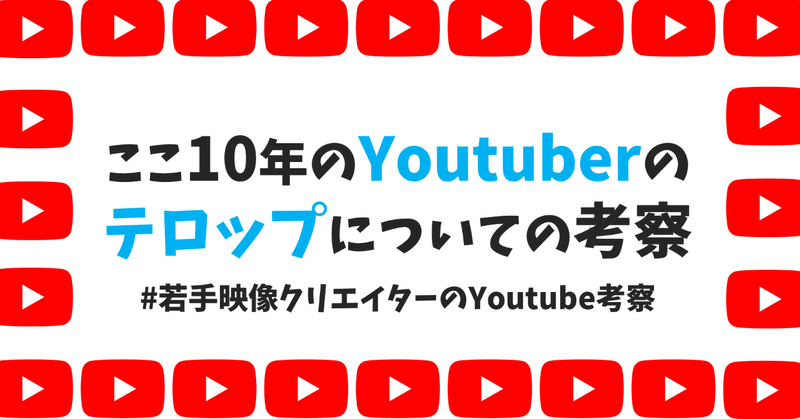
テロップ フォント
テロップを入れた時に、四角く文字化けしてしまう時は フォントを日本語に変える と入力できます。 テロップのフォントは、ソースパネル内のエフェクトコントロール→テキスト→ソーステキストで変更可能です。 テロップに色をつける.
テロップ フォント. YouTuberにもオススメ!映像・動画、テロップにオススメのフォント・書体を紹介 書体をテロップで見かける縁取りにしてみた「明朝体」編 書体をテロップで見かける縁取りにしてみた「ゴシック体」編 明朝体7ウェイトがフリー(無料)で使えるオープンソースフリーフォント「源ノ明朝. テロップを少し意識して見やすくするだけでも 動画のクオリティは一気に高まります! 今回は動画制作者向けに 読みやすいテロップの作り方の例を紹介したいと思います。 フォント サイズ 太さ 色 背景 装飾 レイアウト 行間 カーニング 改行 表示時間. 使用フォント:游ゴシック体 Bold ↓アピアランス設定↓ 左下の「新規線を追加」「新規塗りを追加」「新規効果を追加」ボタンからすべて作成していきます。 テロップ例その2:ハッキリしていて読みやすいデザイン 2つ目は、縁や影が強い固めのデザイン.
さっそく日本語のフリーフォントで商用利用可能なものを教えてもらいました。ゴシック・明朝から手書き風まで、49種のフォントをご紹介します。プロのデザイナーも使用するスゴいフォントがそろってます。 1 ゴシック系 m fonts. 使用フォント:游ゴシック体 Bold ↓アピアランス設定↓ 左下の「新規線を追加」「新規塗りを追加」「新規効果を追加」ボタンからすべて作成していきます。 テロップ例その2:ハッキリしていて読みやすいデザイン 2つ目は、縁や影が強い固めのデザイン. Youtube動画の字幕(テロップ)におすすめの無料フォント 動画の内容をわかりやすくしたり、見やすくしたりする字幕(テロップ)は、飽きさせないためのテクニックのひとつです。 字幕におすすめのフォントは、崩れた特徴的なフォントより、見やすいフォントを使うことが重要です。 字幕が見にくかったりテキトーなフォントを使っていたりすると動画を最後.
テロップのフォントや色、大きさを設定する方法は幾つかあります。 今回は、 エッセンシャルグラフィックス を使って設定していきます。 個人的には一番使いやすいと思います。. 動画に彩りを添える「フォント」 動画にテロップや字幕といった文字をつけることで、 観る人に与える情報力が圧倒的に増します。 今はスマホやタブレットで気軽に動画を観られるようになりましたから. 字幕(テロップ)に使えるフォント 源ノ角ゴシック(げんのかくごしっく)(Source Han Sans) ダウンロード 見やすくて使いやすいフォントで、いろいろなところで使えます。一番の定番フォントです。 太い方が動画内では見やすいので、Boldで使っています。.
今回の記事はフォントについてです。 デフォルトのフォントをそのまま使っていませんか? フォント1つで動画の印象は大きく変わります。 今回は以下の条件の元、YouTubeのテロップにおすすめのものを選んでみました。 ・無料 ・商用利用可 ・ひ. YouTuberにもオススメ!映像・動画、テロップにオススメのフォント・書体を紹介 書体をテロップで見かける縁取りにしてみた「明朝体」編 書体をテロップで見かける縁取りにしてみた「ゴシック体」編 明朝体7ウェイトがフリー(無料)で使えるオープンソースフリーフォント「源ノ明朝. テロップのフォントや色、大きさを設定する方法は幾つかあります。 今回は、 エッセンシャルグラフィックス を使って設定していきます。 個人的には一番使いやすいと思います。.
「雲」 は、字幕(テロップ)をデコレーションしたように表示できるフォントです。 自分で表示される素材を作ることは、なかなか難しいですよね。 しかしimovieのツールを使えば、このようなデザイン性のある字幕も簡単に制作できます。. ニューステロップ基本書体一覧 都道府県 nnn jnn fnn ann txn nhk 東京 ヒラギノ角ゴウインクスlイワタ新ゴナウg tbs ゴシックtp(axis)ネオツデイ ud新ゴntロダン. そしてこのフォントは 最初に全て決めておきましょう テロップを入れるたびにフォント何にしようかな〜と選ぶ時間がもったいないです 時間短縮のためにもフォントを決めておく事をオススメします 状況に応じたおすすめのフリーフォントを一部紹介.
テロップのフォントや色、大きさを設定する方法は幾つかあります。 今回は、 エッセンシャルグラフィックス を使って設定していきます。 個人的には一番使いやすいと思います。. 第1章:テロップパズル さっそくワークショップをはじめましょう。 ルールはカンタンです。ベースやフォント・色・テクスチャーなど、あなたの好きなものを自由に組み合わせてテロップを作るというもの。 パズルみたいな遊びだと思って参加してもらえればうれしいです。. テロップのフォントや色、大きさを設定する方法は幾つかあります。 今回は、 エッセンシャルグラフィックス を使って設定していきます。 個人的には一番使いやすいと思います。.
ニューステロップ基本書体一覧 都道府県 nnn jnn fnn ann txn nhk 東京 ヒラギノ角ゴウインクスlイワタ新ゴナウg tbs ゴシックtp(axis)ネオツデイ ud新ゴntロダン.